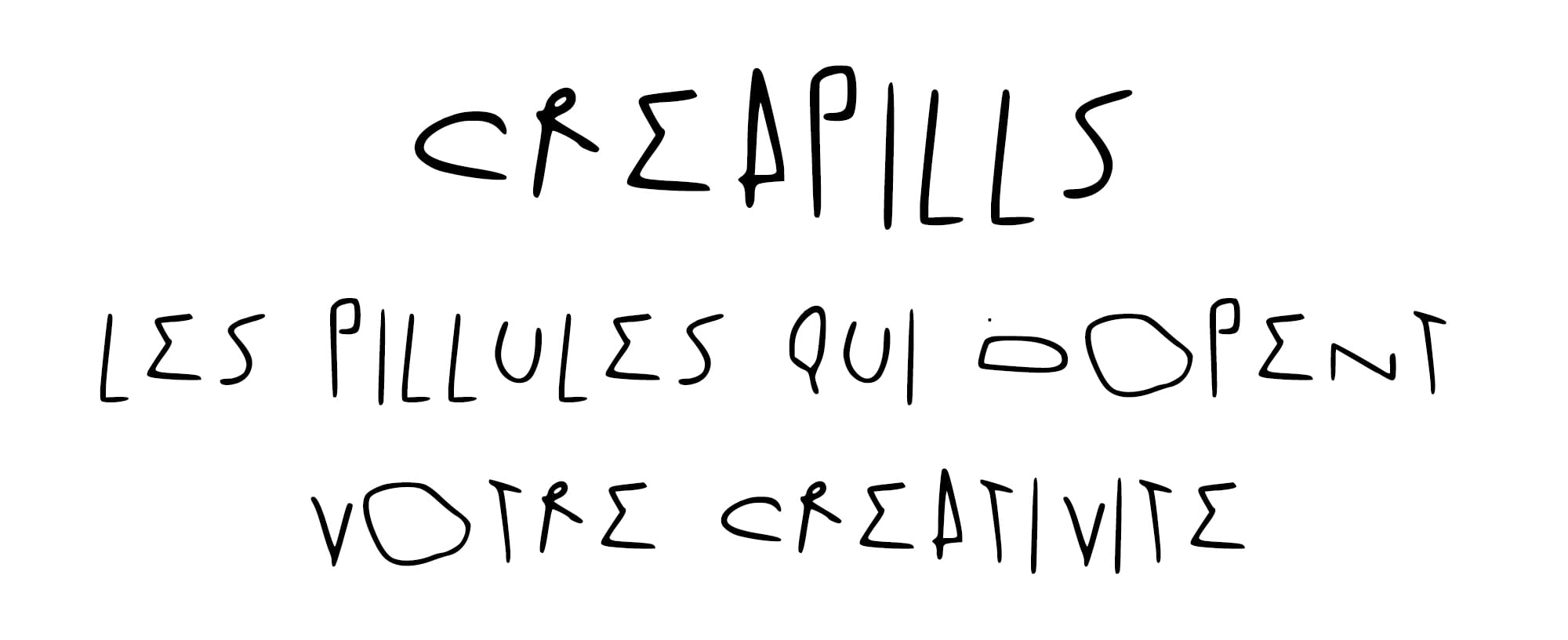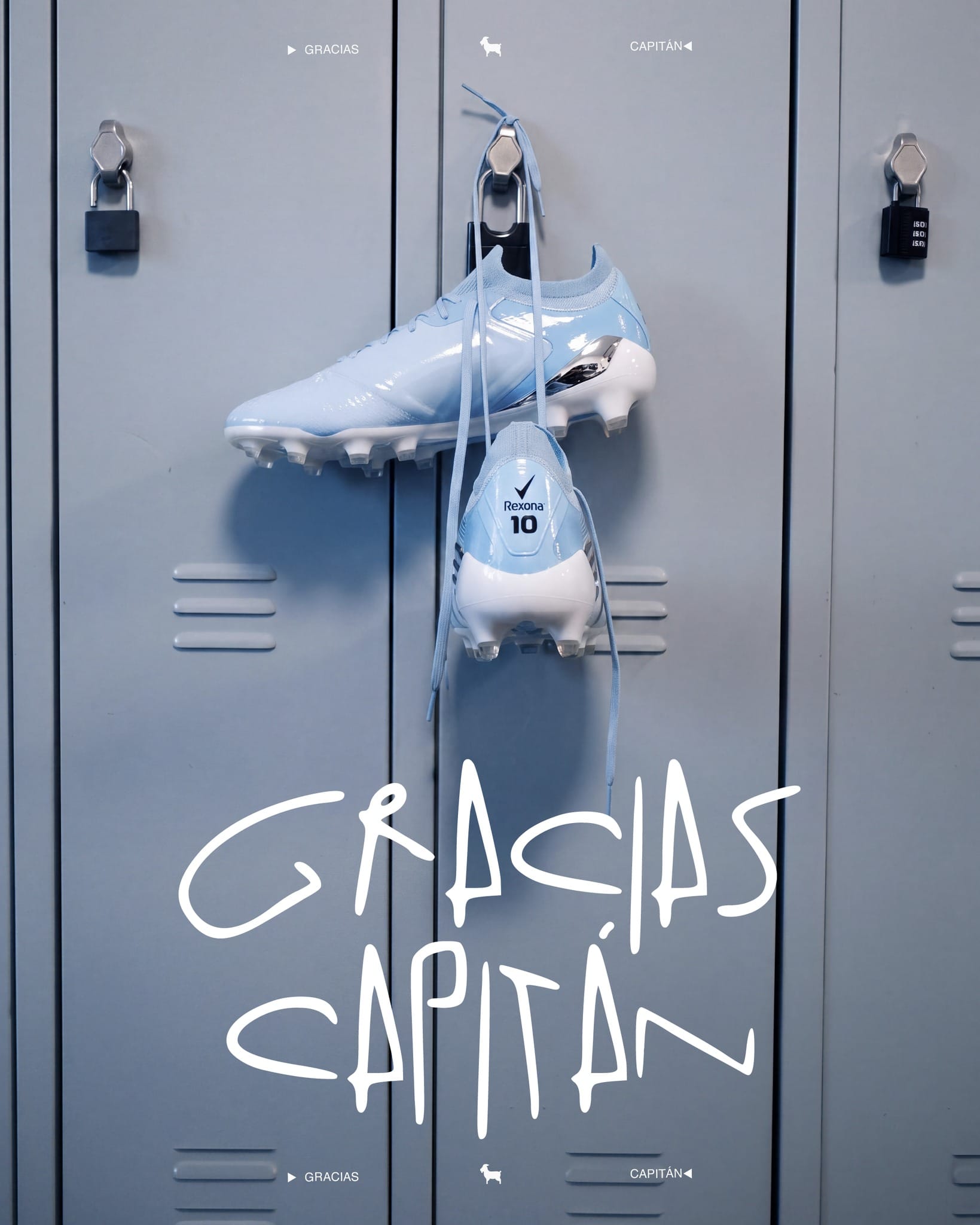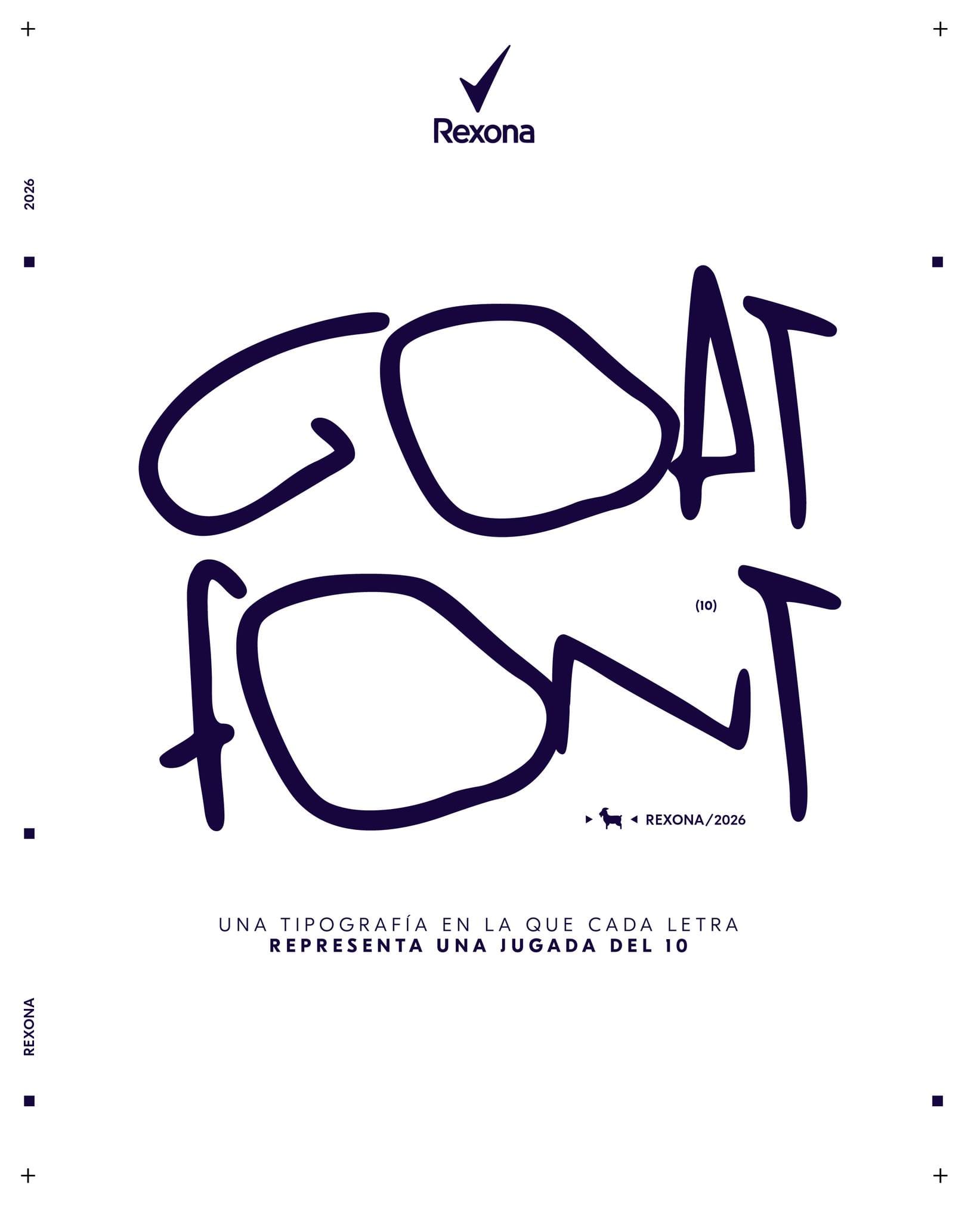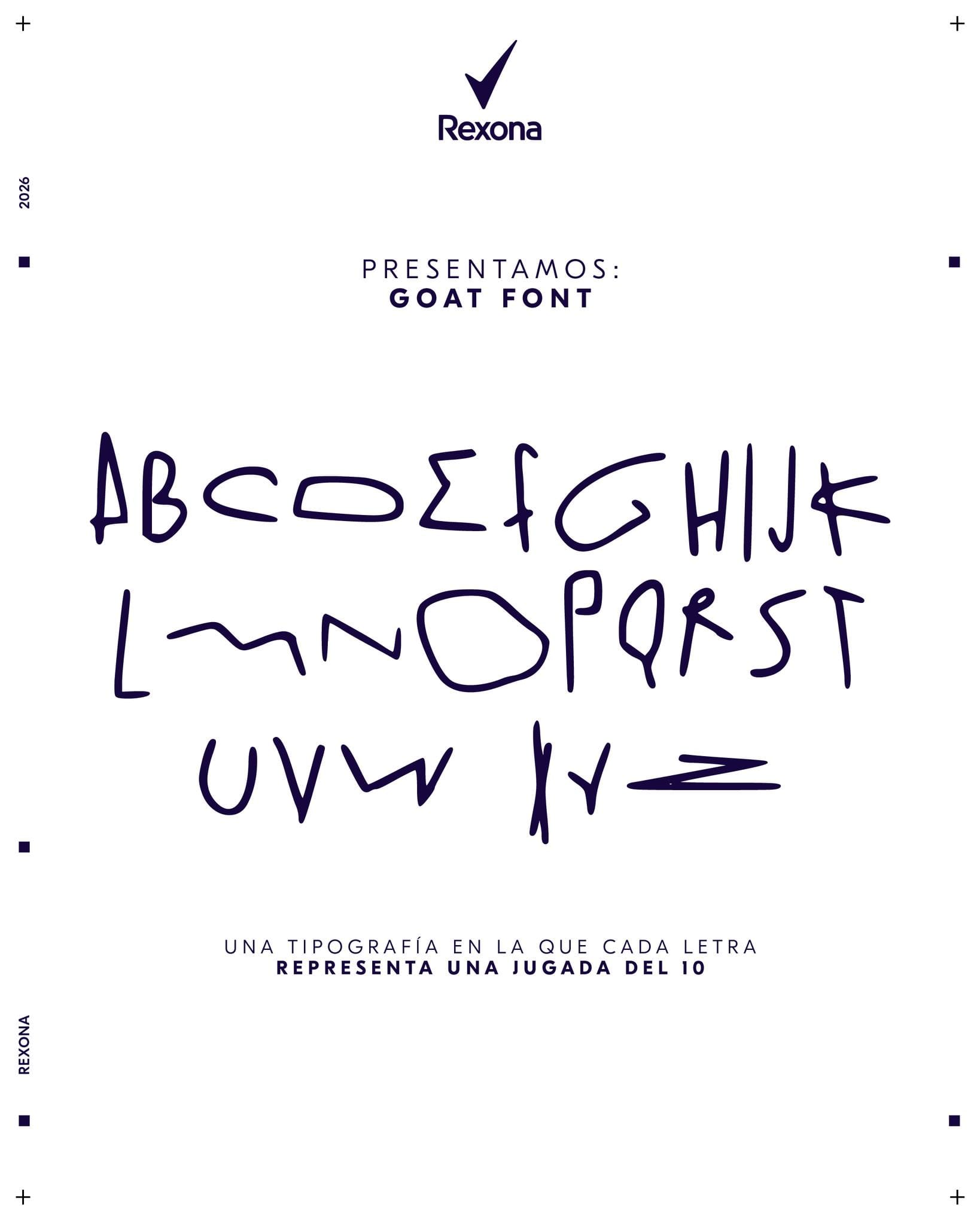
Pendant vingt ans, Lionel Messi a tracé sur les pelouses des lignes que personne n’arrivait à anticiper. Rexona Argentina a eu l’idée de récupérer ces trajectoires et d’en faire autre chose : une typographie complète, baptisée GOAT Font, où chaque lettre est née d’une action réelle disputée sous le maillot de l’Albiceleste.
La marque a dévoilé le projet sur son compte Instagram, quelques jours après l’annonce par Messi de sa retraite internationale, le 31 août. Une carrière ouverte en 2005, refermée sur 125 buts en 207 sélections, deux Copa América et le titre mondial de 2022.
Une donnée de terrain convertie en signe graphique
Le principe tient dans une conversion. Les changements de direction, les crochets, les courses en profondeur deviennent des tracés typographiques. Certains caractères s’enroulent, d’autres reviennent sur eux-mêmes, exactement comme les lignes de déplacement utilisées dans les analyses tactiques. La matière première n’est pas dessinée, elle est prélevée.
Pourquoi ce n’était pas la signature manuscrite qu’il fallait numériser
L’écueil évident aurait été de vectoriser l’écriture ou l’autographe du joueur. Rexona a choisi l’inverse : ce qui définit Messi n’est pas sa main, c’est sa façon de se déplacer. En allant chercher le geste plutôt que l’attribut, la marque signe un dispositif créatif qui dit quelque chose de son sujet au lieu de simplement l’illustrer.
Rexona n’a publié aucune légende associant chaque lettre à un match précis. Le décodage est laissé aux supporters, invités à confronter les formes aux images d’archives. C’est une stratégie d’engagement peu coûteuse et efficace : elle transforme un objet graphique fini en conversation continue, alimentée par les fans eux-mêmes.
Le fichier est proposé en téléchargement libre. La campagne cesse alors d’être une prise de parole pour devenir un outil : affiches, hommages, visuels de fans circulent avec, dans leur ADN, une marque de déodorant qui ne s’affiche nulle part.
La plupart des activations liées à une retraite sportive vivent quarante-huit heures. Celle-ci a une durée de vie indexée sur celle d’un fichier installé sur des milliers d’ordinateurs. Rexona ne commémore pas un départ, elle laisse aux supporters argentins de quoi continuer à écrire avec. Pour tester la typographie GOAT Font, rendez-vous sur le site argentin de Rexona.